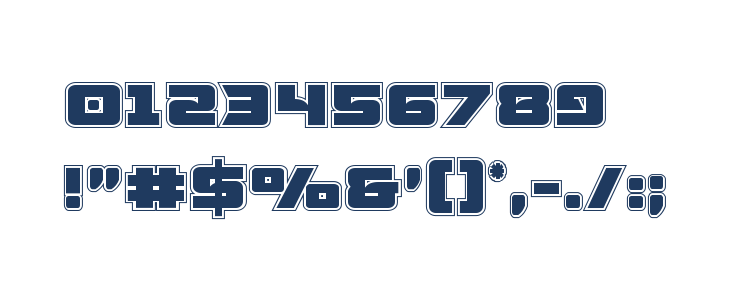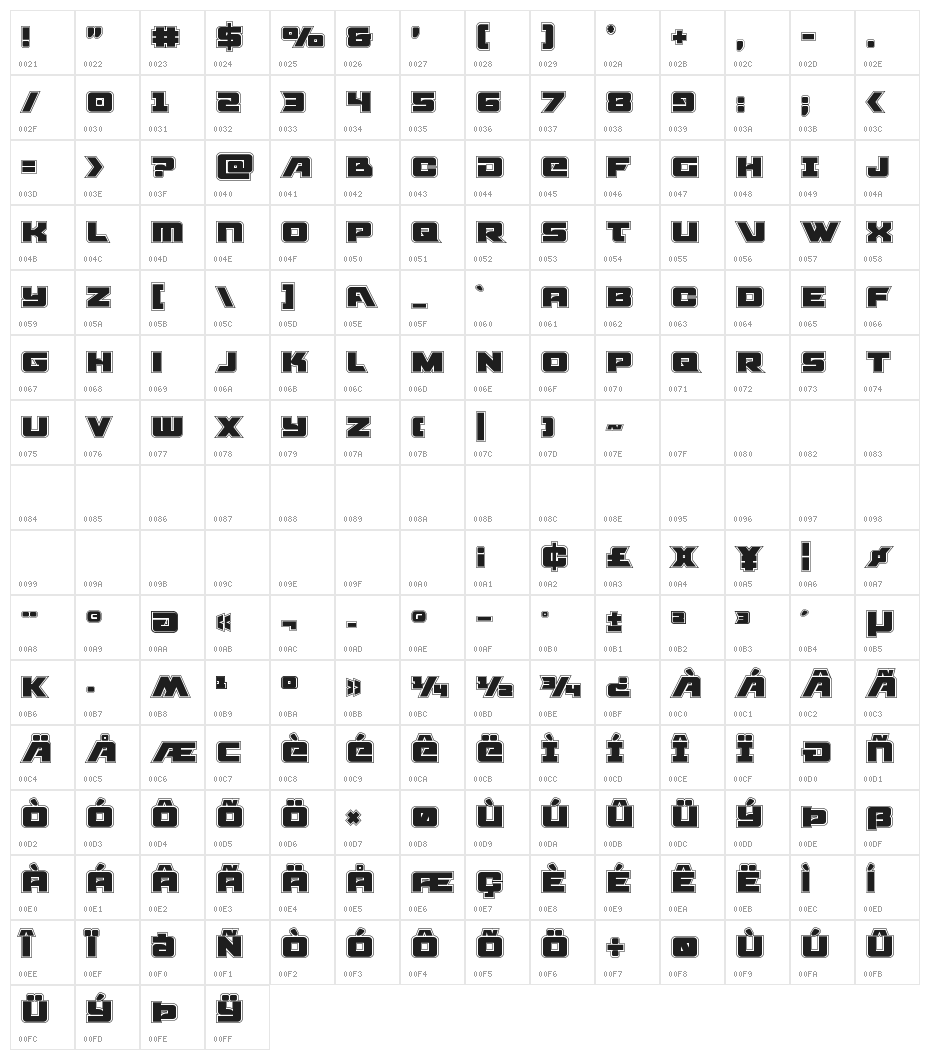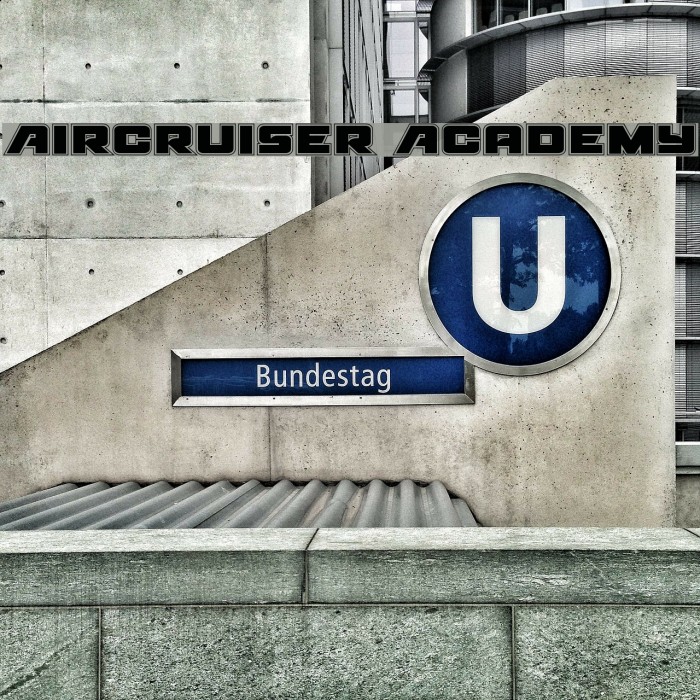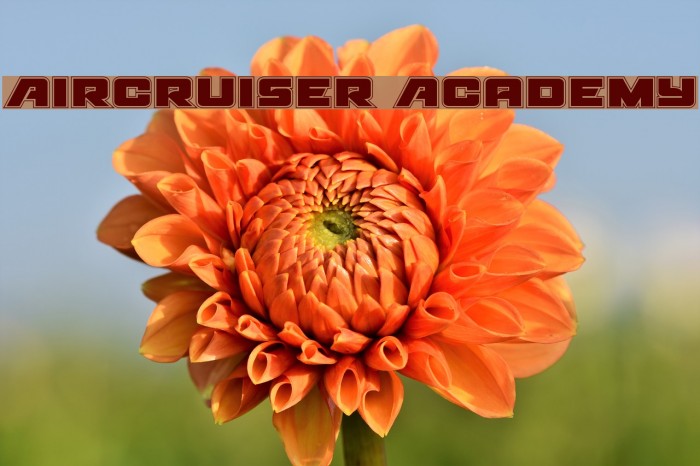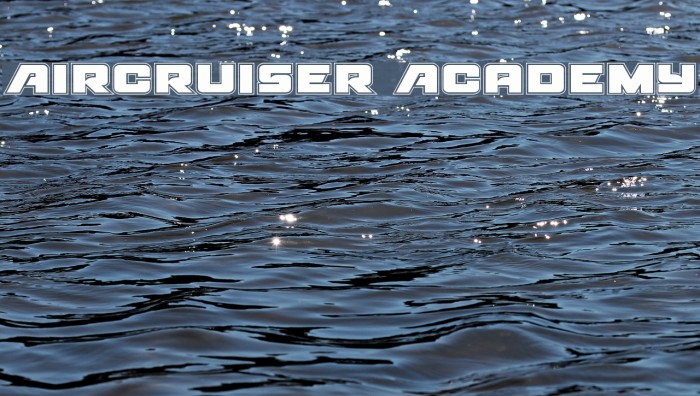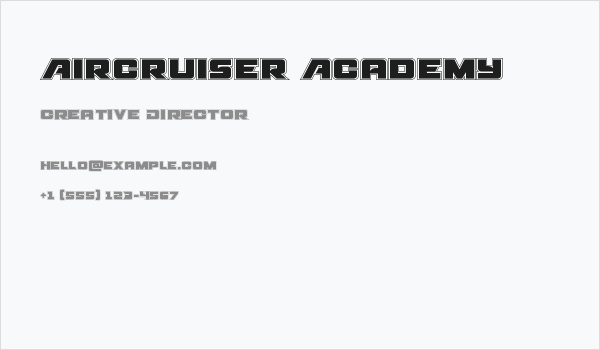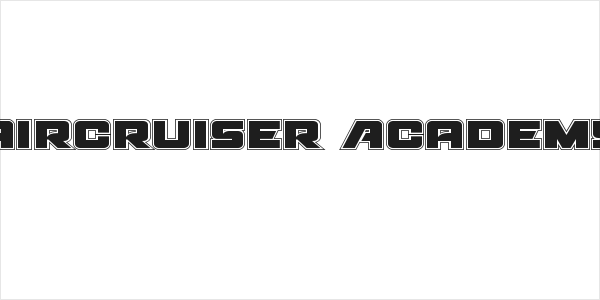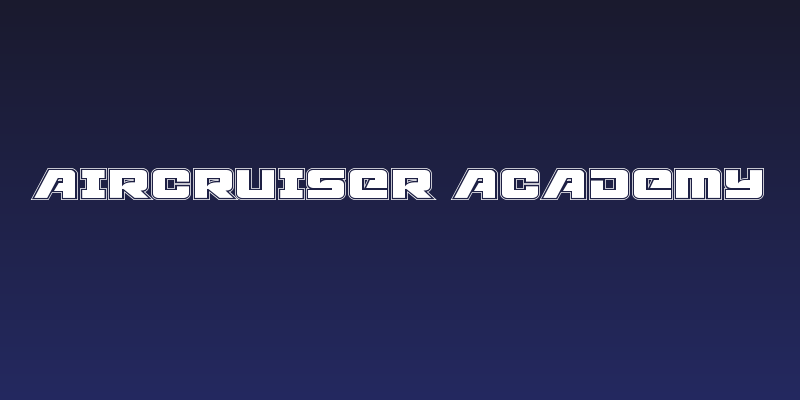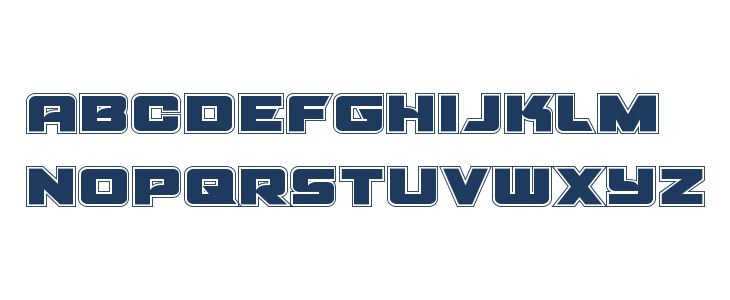
Aircruiser Academy Font
✎ Outline
| مشاريع مقترحة | Ideal for projects requiring a modern, industrial look such as tech branding, video game titles, or futuristic posters. |